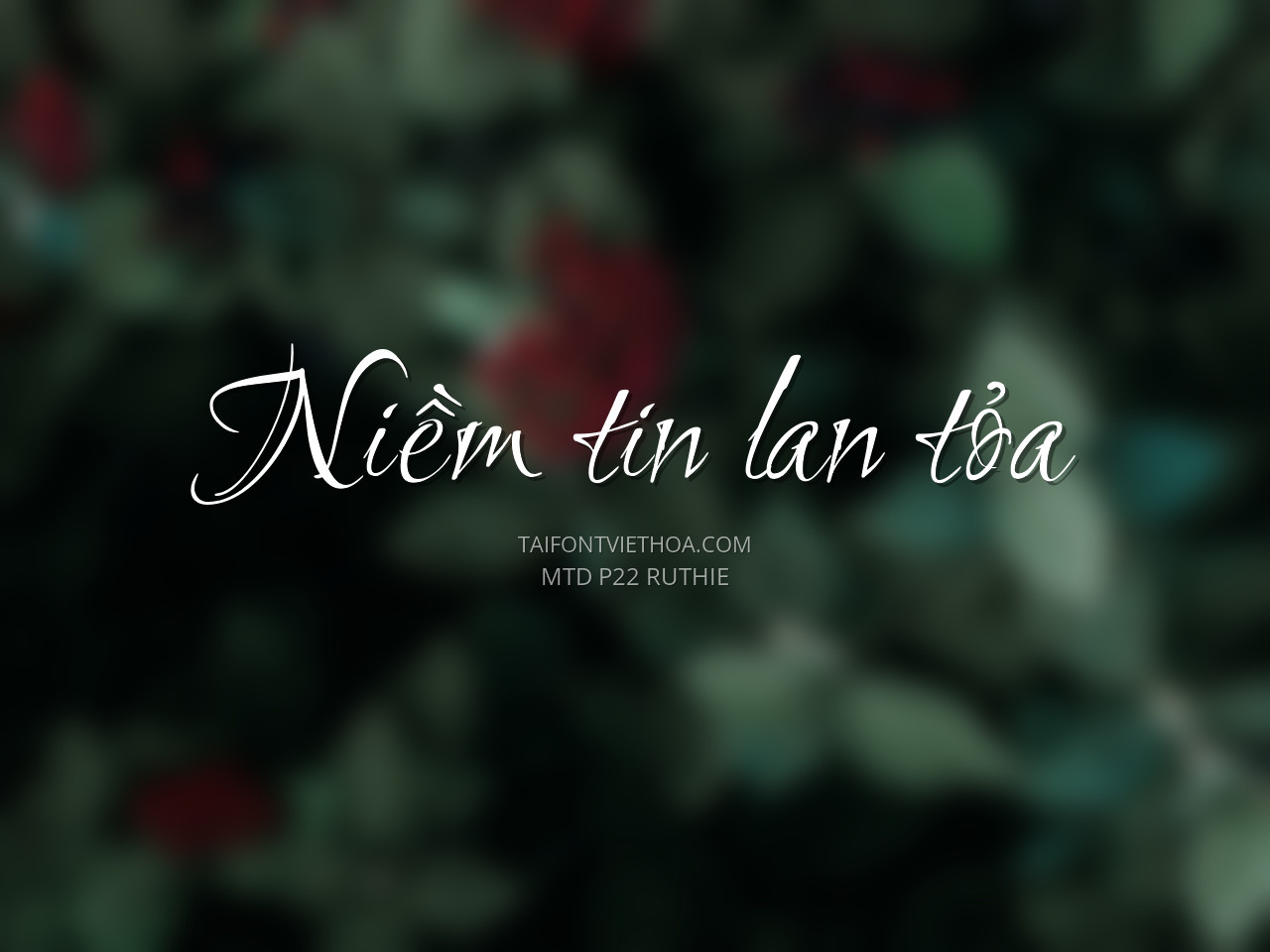
Font việt hóa MTD P22 Ruthie
Tác giả Font: Typesetit
Giới thiệu về font P22 Ruthie
P22 Ruthie là một font script thanh lịch mang phong cách cổ điển, được thiết kế bởi Rob Leuschke cho hãng P22 Type Foundry – một thương hiệu nổi tiếng chuyên về các kiểu chữ nghệ thuật và độc đáo. Ruthie kết hợp giữa nét viết tay mềm mại và yếu tố serif nhẹ, tạo nên một dáng chữ vừa duyên dáng vừa chuyên nghiệp. Font đặc biệt phù hợp với những thiết kế cần thể hiện sự tinh tế, nữ tính và sang trọng. Phiên bản Việt hóa do Motokiwo Type (MTD) thực hiện, hỗ trợ đầy đủ tiếng Việt cùng hơn 70 ngôn ngữ khác trên toàn thế giới.
Đặc điểm thiết kế và ứng dụng của font P22 Ruthie
Ruthie nổi bật với nét viết uyển chuyển, cấu trúc chữ mềm mại cùng các ligatures và swashes đi kèm tạo nên độ chuyển động tự nhiên. Các ký tự có độ nghiêng nhẹ, thể hiện sự duyên dáng, dễ đọc và rất phù hợp khi sử dụng làm tiêu đề, chữ ký thương hiệu hoặc nội dung cá nhân hóa.
Ứng dụng tiêu biểu của P22 Ruthie gồm: thiết kế thiệp mời, bìa sách lãng mạn, logo thương hiệu cá nhân, tiêu đề blog thời trang – làm đẹp, bao bì mỹ phẩm, sản phẩm handmade và dự án sáng tạo hướng đến nữ giới. Ngành nghề lý tưởng: cưới hỏi, spa, thời trang, mỹ phẩm, quà tặng nghệ thuật và truyền thông thương hiệu nữ tính.